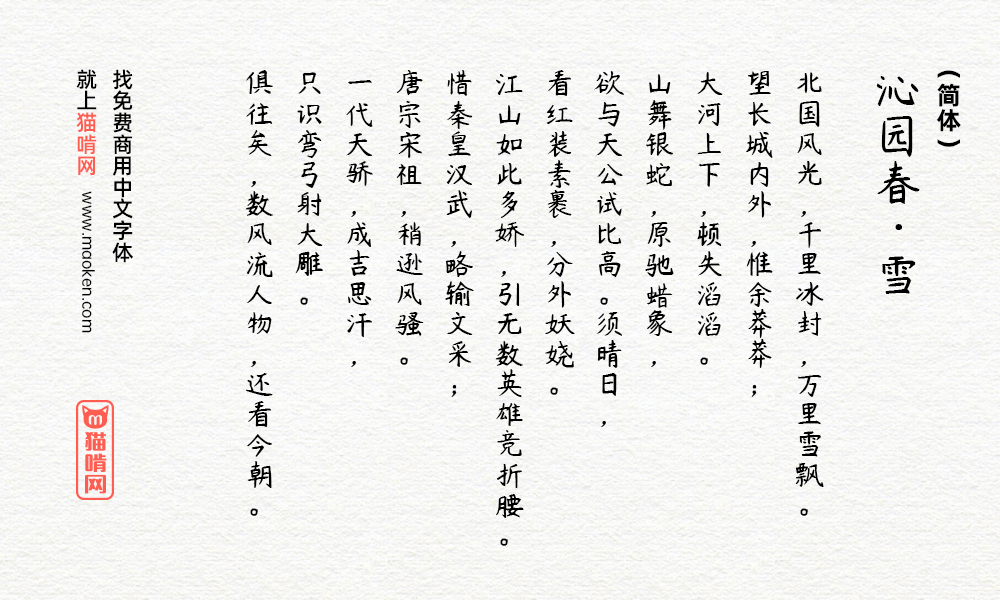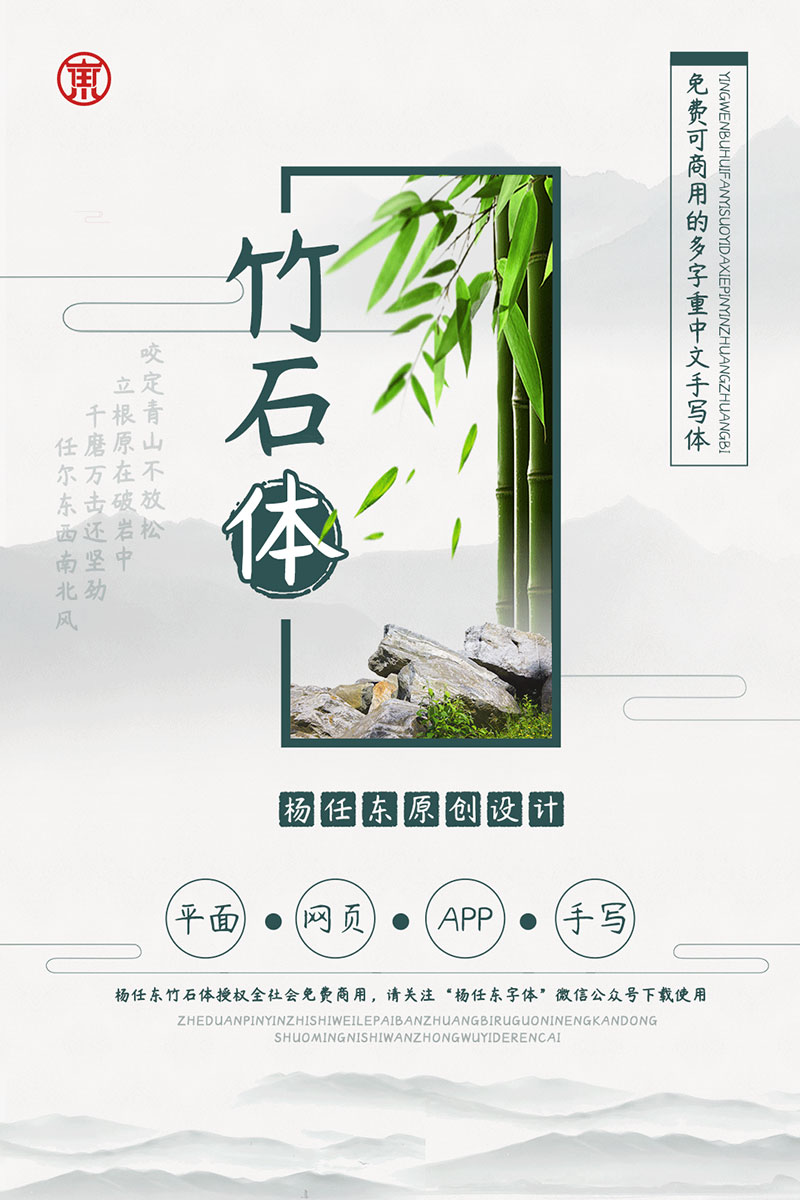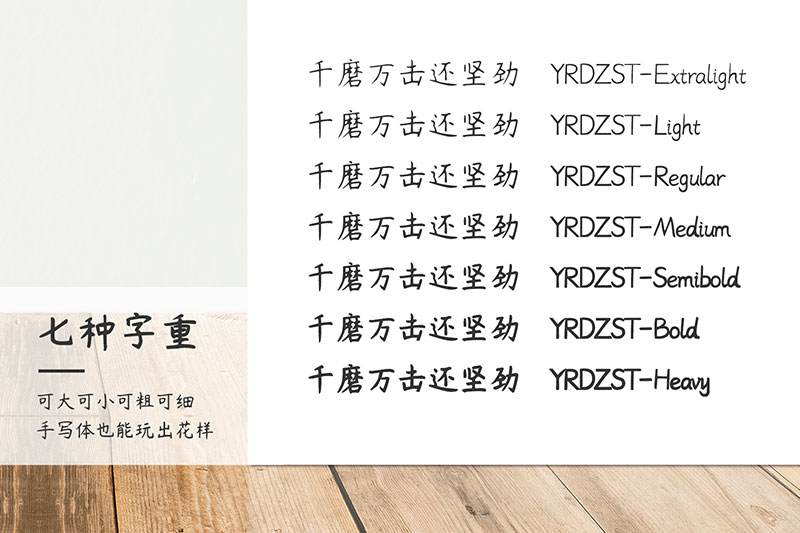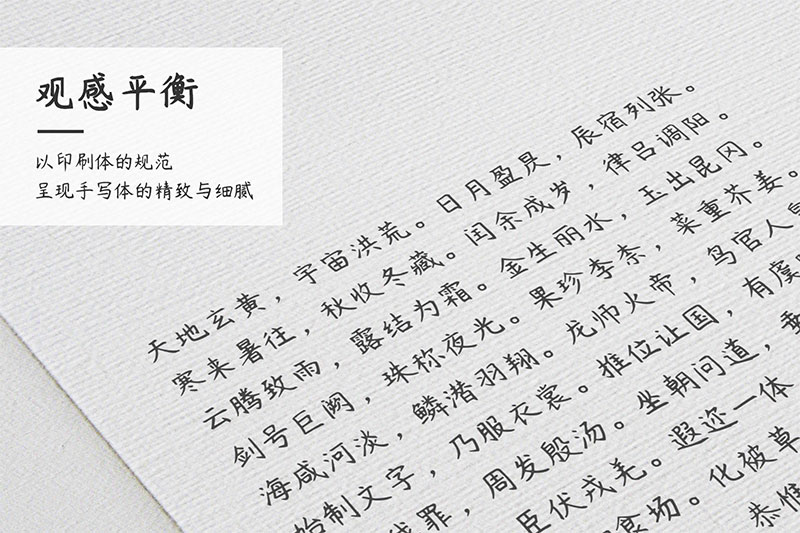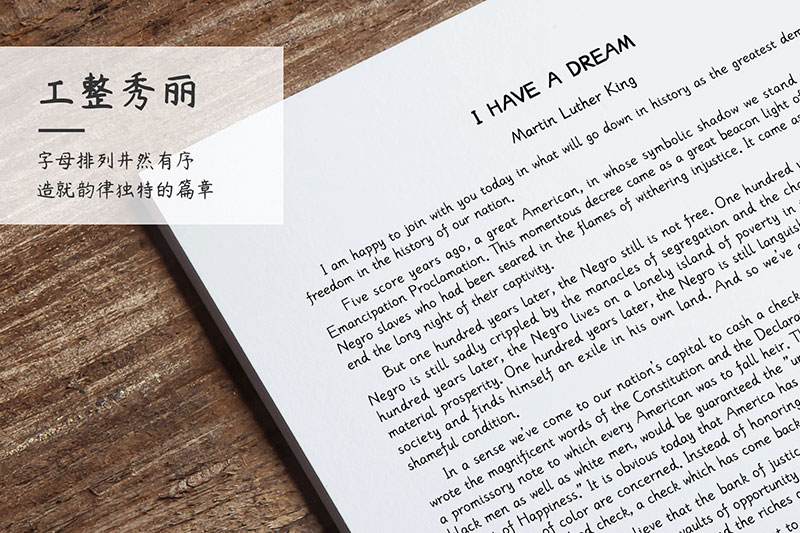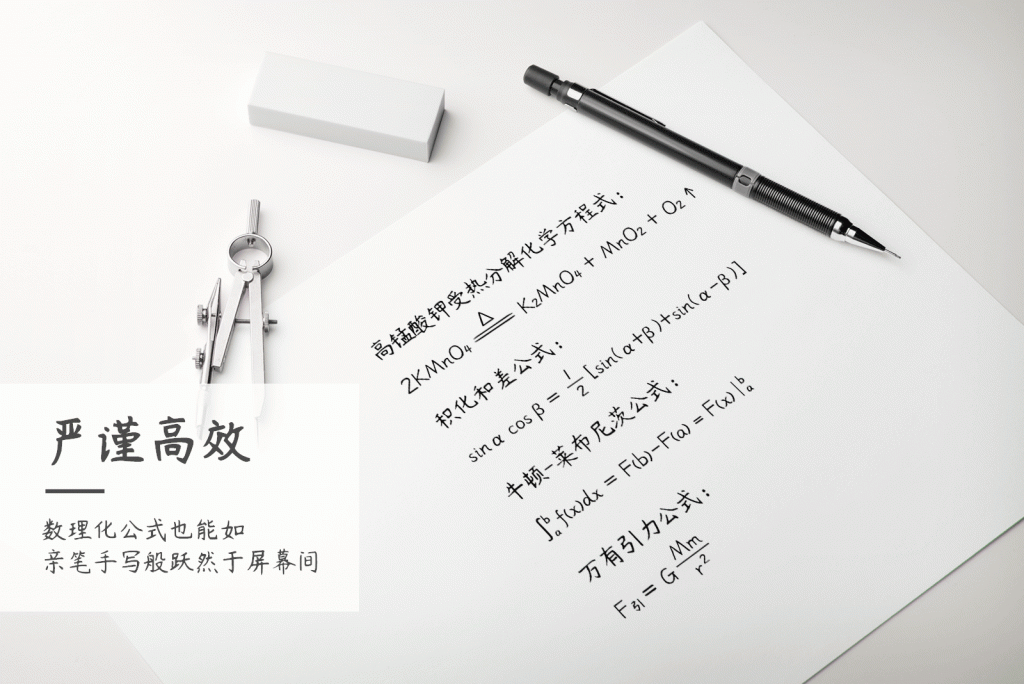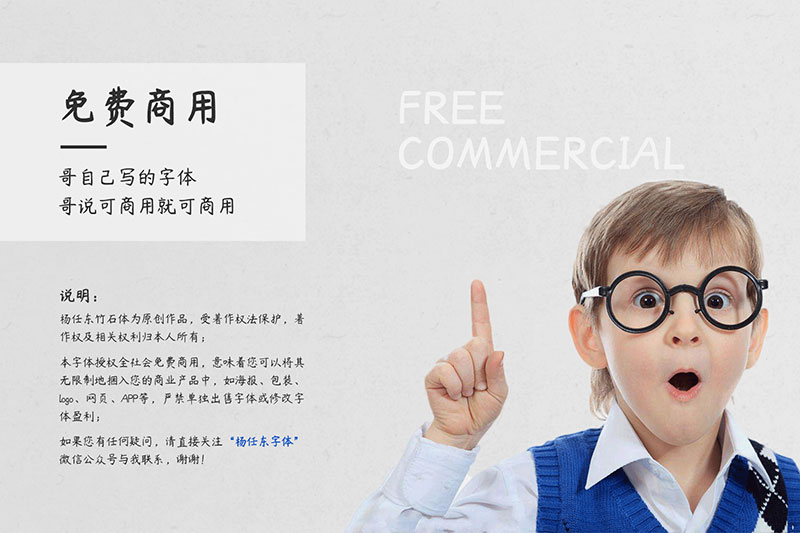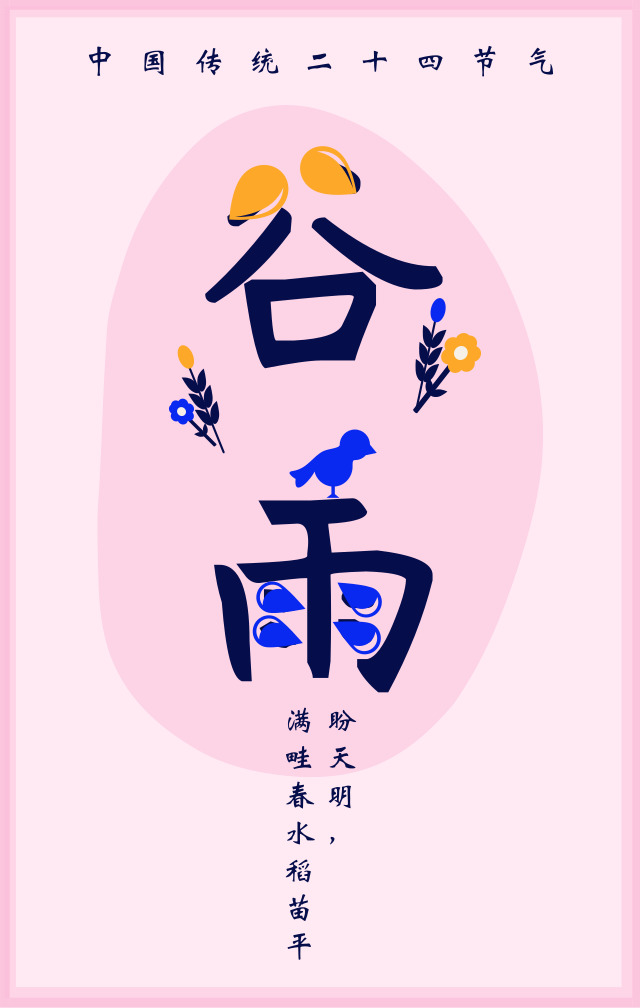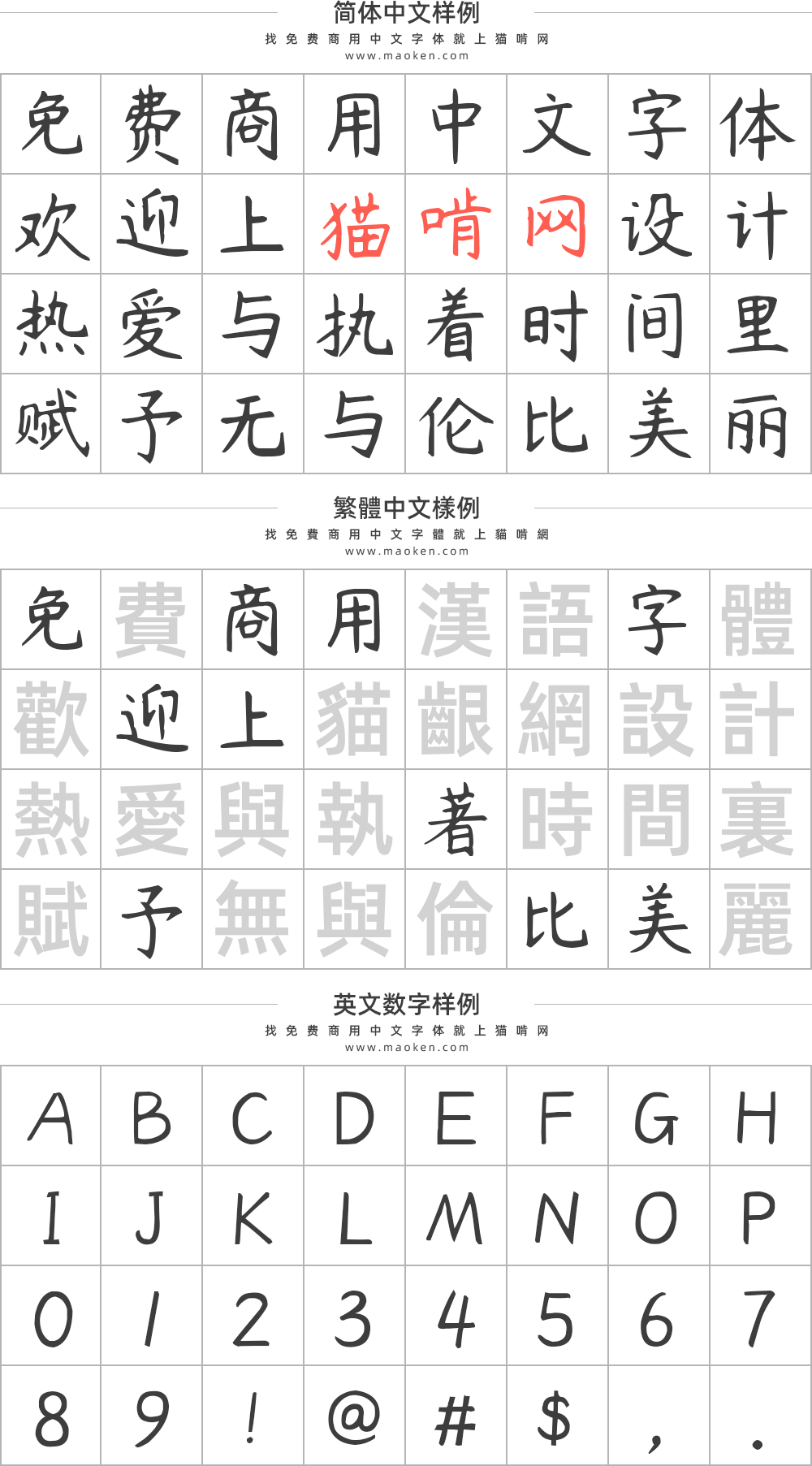
杨任东竹石体:一款具有7字重的免费可商用的手写字体
字体作者:杨任东 (中国大陆) 字体字重:7个
拿字体版权问题来说,形势可谓十分严峻。高额的字体授权费用和许多版权归属不明朗的字体始终困扰着设计师。而现实情况是免费可商用的字体少之又少,字体盗版情况屡禁不止。那么字体还能不能好好用了?答案当然是:能!全球首款七字重中文手写字体,杨任东竹石体正式发布!重点是,免费可商用!!!
杨任东竹石体按照GB2312-80书写,并增补了少量常见汉字,单个ttf格式字体文件包括7311个字符,涵盖了日常生活用字99.8%的需求;整套字体有7个字重,也就是共有7个ttf格式字体文件,全套字体共计50000余个字符。
字体设计理念
这字体有个大毛病:字重数值在乱搞!致使 Ps 没法正常使用全部字重。
不過還有個簡繁版竹石體呢!